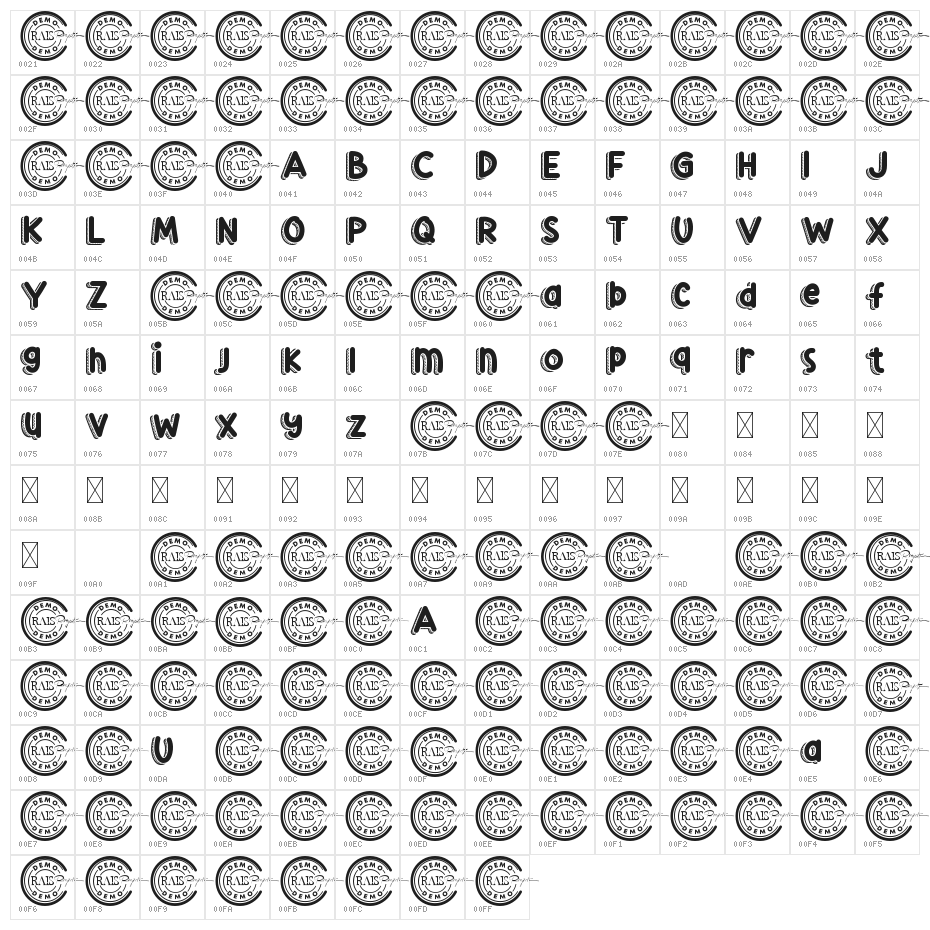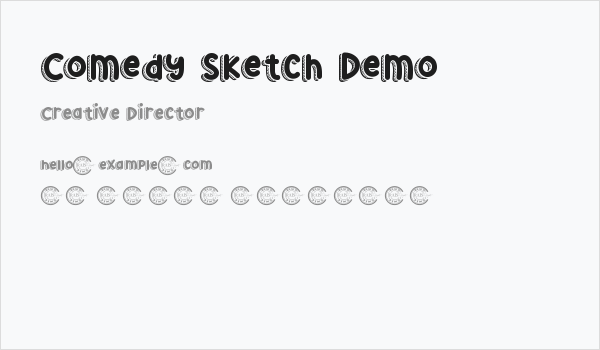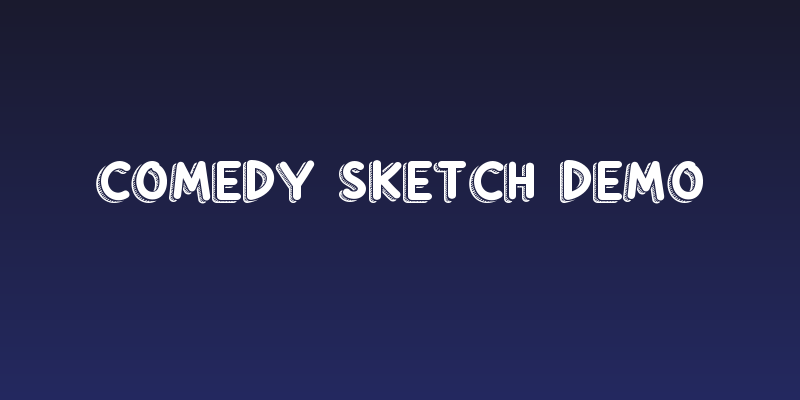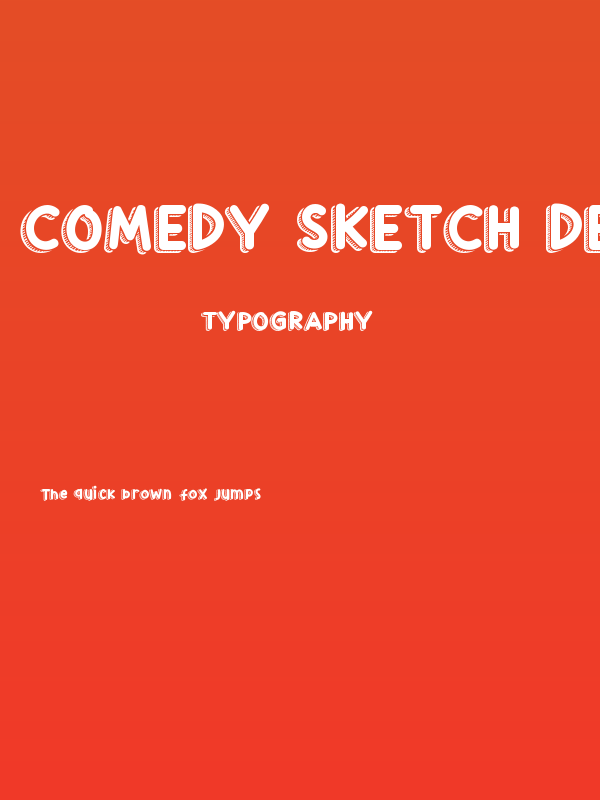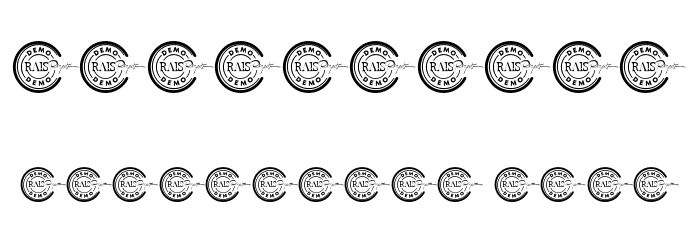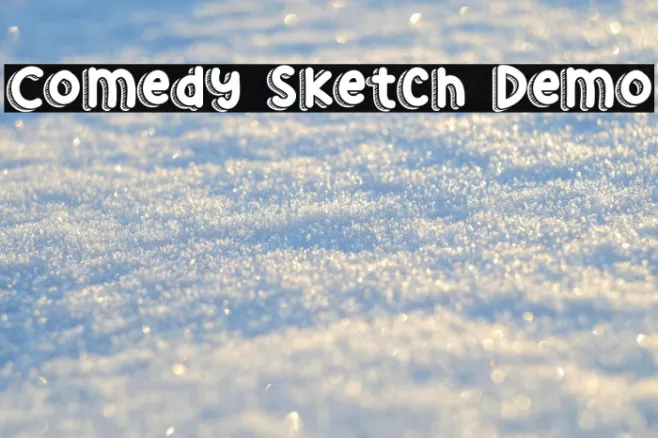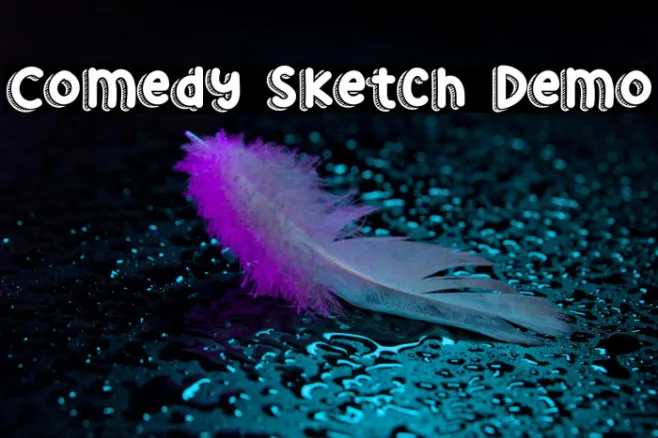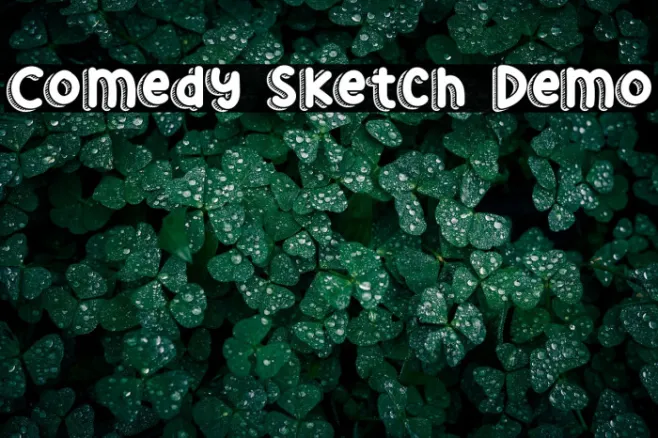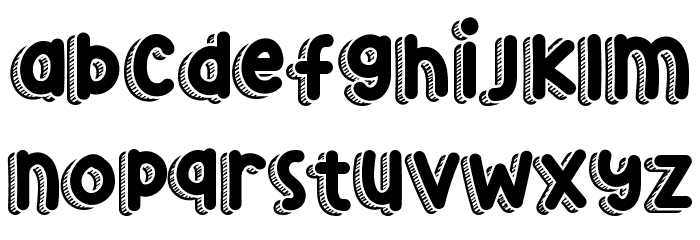
Comedy Sketch Demo Font
| Style général | Playful, Hand-drawn |
| Projets proposés | Ideal for children's books, comic strips, playful branding, and creative posters. |